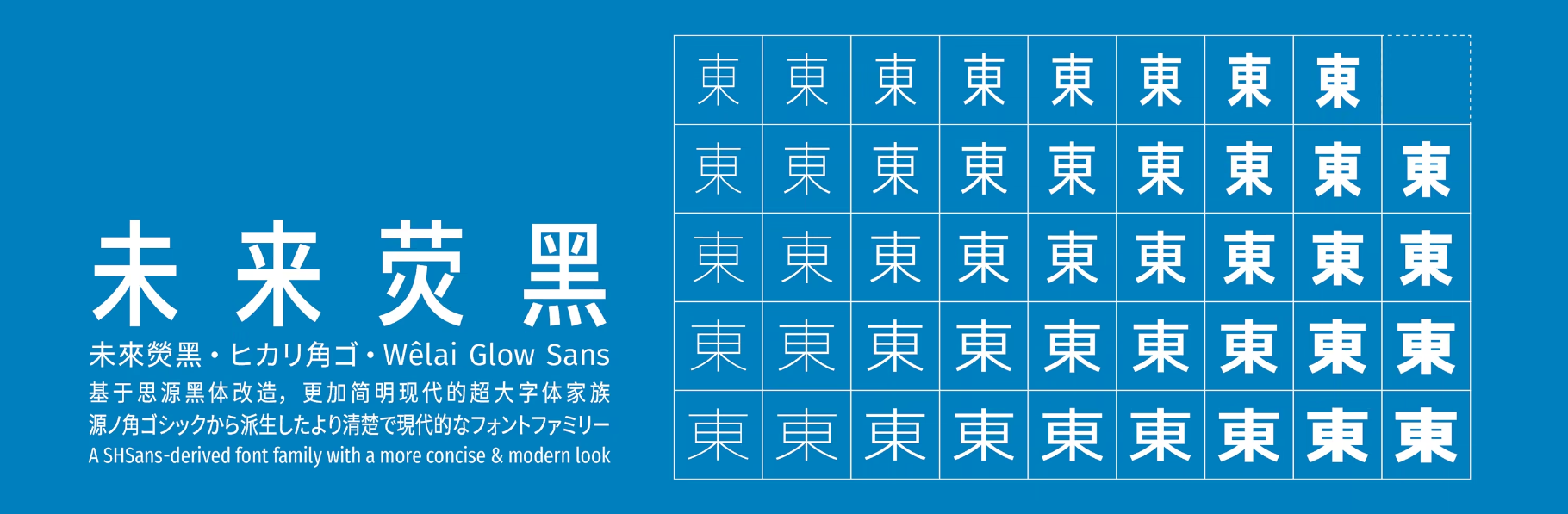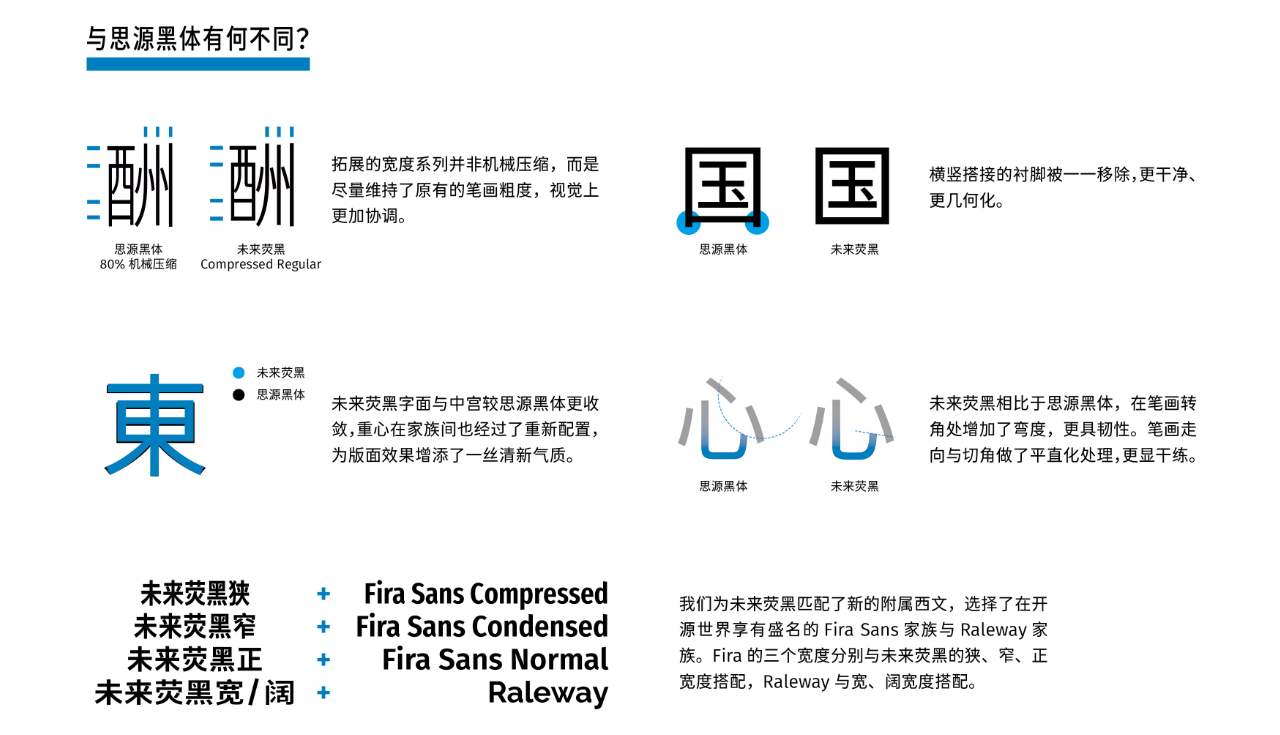
未来荧黑(Glow Sans)是以思源黑体为基底,融合 Fira Sans 与 Raleway 字体,通过图像处理算法和字形建模设计的一种开源字体项目。
未来荧黑将原来的 7 种字重扩展为 9 种(从 ExtraLight 到 Heavy),并新增 5 种宽度系列(压缩、紧凑、常规、扩展、宽体),总共44款字体,涵盖了简体中文、繁体中文和日文。
相比于思源黑体,未来荧黑的中宫与字面更加收敛,字重之间经过了重新配置,笔画细节上处理得更加干净,排版效果简明清晰。但是,由于某些字符在宽度系列处理时难度较大,所以对其进行暂时剔除,如果出现个别思源黑体支持的字在未来荧黑不显示属于正常现象。